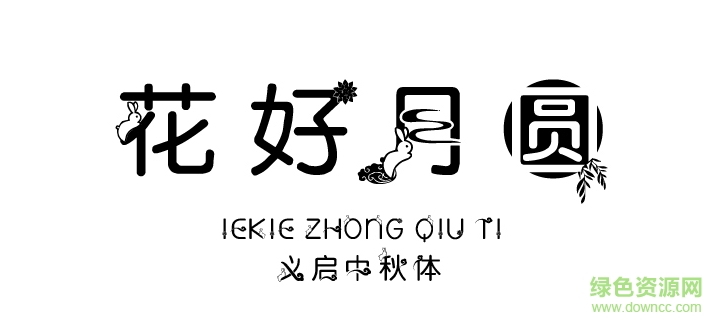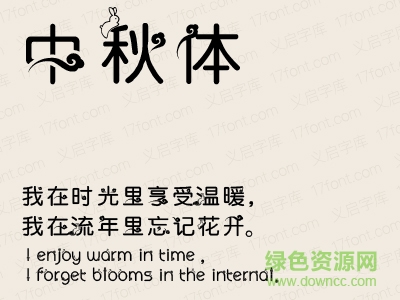
義啟中秋體是一款實(shí)時(shí)應(yīng)景系列的特別版義啟字體,為了慶祝中秋佳節(jié)專(zhuān)門(mén)設(shè)計(jì)的這款字體,需要的朋友歡迎來(lái)綠色資源網(wǎng)下載使用!
這是一款為慶祝中秋所特別制作的字體,融入祥云、玉兔、燈籠、圓月等元素,不僅更具神話(huà)色彩,更渲染出中秋的氛圍。讓使用這款字體的人在享受字體美的同時(shí)感受節(jié)日的喜慶。